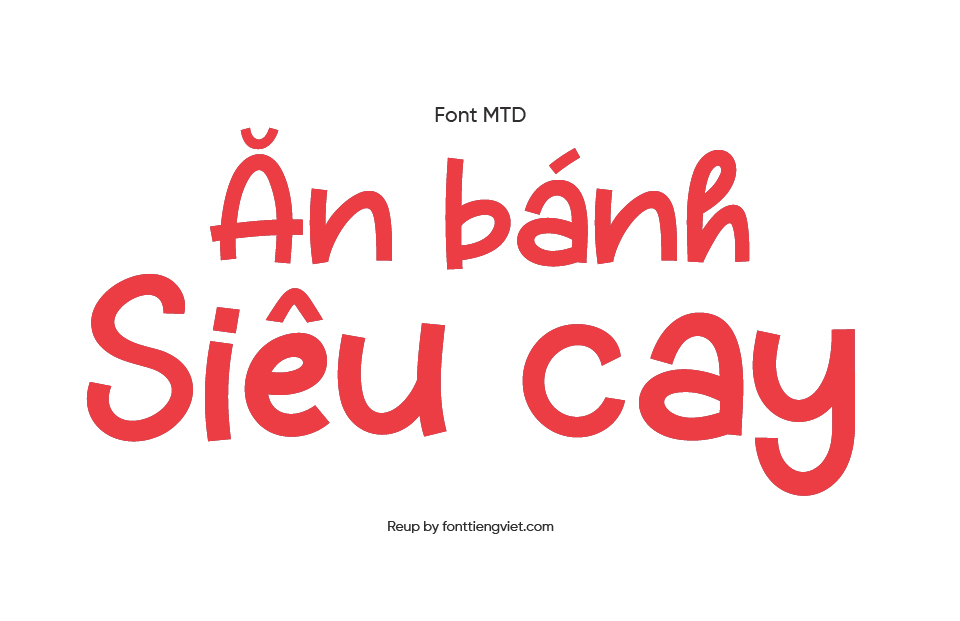
Trong thế giới thiết kế đồ họa và sáng tạo nội dung số, việc lựa chọn Font Chữ phù hợp đóng vai trò then chốt trong việc truyền tải thông điệp. Một xu hướng nổi bật gần đây là việc sử dụng các phông chữ thủ công (handwritten) hoặc phông chữ hiển thị (display font) với phong cách độc đáo, tươi mới. Chính vì lẽ đó, cộng đồng thiết kế Việt Nam đã đón nhận nồng nhiệt sự xuất hiện của Font Việt hóa MTD Cheese Sauce. Đây không chỉ là một phông chữ thông thường, mà còn là một công cụ giúp các bạn học sinh, sinh viên, đặc biệt là những người đang chuẩn bị cho các đồ án tốt nghiệp hoặc bài thuyết trình quan trọng, nâng cao tính thẩm mỹ và sự chuyên nghiệp cho tác phẩm của mình. Phông chữ này đã được Việt hóa kỹ lưỡng, đảm bảo khả năng hiển thị hoàn hảo các ký tự tiếng Việt có dấu, mang lại sự linh hoạt tối đa cho người dùng.
Khám Phá Sức Hút Đặc Biệt Của Font Việt hóa MTD Cheese Sauce
MTD Cheese Sauce là một phông chữ mang đậm chất cá nhân hóa, thường được xếp vào nhóm phông chữ viết tay (handwritten) hoặc brush script. Điểm mạnh lớn nhất của nó nằm ở sự ngẫu hứng và nét cọ mạnh mẽ, mô phỏng chân thực cảm giác viết bằng tay. Khi được “Việt hóa” (chuyển đổi và bổ sung các ký tự tiếng Việt), Font Việt hóa MTD Cheese Sauce không chỉ giữ nguyên được linh hồn ban đầu mà còn trở nên hữu ích hơn gấp bội cho thị trường nội địa. Sự Việt hóa chuyên nghiệp đảm bảo rằng tất cả các dấu thanh, dấu mũ, và các ký tự đặc biệt của tiếng Việt đều được tích hợp mượt mà, không gây lỗi hiển thị hay mất cân đối về mặt thị giác (optical balance). Phông chữ này rất phù hợp với các thiết kế đòi hỏi sự vui tươi, năng động, và một chút phá cách, ví dụ như thiết kế bao bì sản phẩm, thiệp mời sự kiện, hay các ấn phẩm quảng cáo dành cho giới trẻ.
Tại Sao Học Sinh, Sinh Viên Cần Quan Tâm Đến Phông Chữ Này?
Đối với học sinh cấp ba và sinh viên đại học, việc tạo ra các bài tiểu luận, báo cáo hoặc đồ án có tính thẩm mỹ cao ngày càng trở nên quan trọng. Một phông chữ độc đáo như MTD Cheese Sauce có thể giúp bài thuyết trình của bạn nổi bật hơn giữa đám đông. Thay vì chỉ sử dụng các phông chữ phổ thông, việc áp dụng phông chữ này vào các tiêu đề, trích dẫn nổi bật hoặc các tài liệu quảng bá cho câu lạc bộ sẽ tạo ra dấu ấn mạnh mẽ. Các dự án nghệ thuật, tạp chí tường, hay thiết kế áo lớp cũng là những ứng dụng hoàn hảo cho phông chữ mang phong cách typography hiện đại này. Sử dụng phông chữ Việt hóa chất lượng cao giúp tiết kiệm thời gian chỉnh sửa lỗi font, cho phép sinh viên tập trung hơn vào nội dung cốt lõi của bài thi hoặc bài báo cáo cuối kỳ.
Ứng Dụng Thực Tiễn Của Phông Chữ Này Trong Học Tập và Thiết Kế
Khả năng ứng dụng của phông chữ Việt hóa MTD Cheese Sauce là rất rộng. Nó vượt ra ngoài phạm vi thiết kế đồ họa chuyên nghiệp và đi vào các hoạt động học thuật hàng ngày. Dưới đây là một số cách mà phông chữ này có thể hỗ trợ hiệu quả cho quá trình học tập và sáng tạo:
- Thiết Kế Poster và Infographic: Giúp các thông tin phức tạp trở nên dễ hiểu và hấp dẫn hơn, rất cần thiết cho các dự án nhóm trong môn Khoa học Xã hội hoặc các lớp Thiết kế Truyền thông.
- Đồ Án Tốt Nghiệp: Tạo điểm nhấn mạnh mẽ cho trang bìa hoặc các phần tiêu đề lớn trong đồ án, thể hiện sự đầu tư nghiêm túc vào mặt hình ảnh.
- Tài Liệu Marketing cho Trường Học/Sự Kiện Sinh Viên: Sử dụng trong các ấn phẩm quảng cáo cho ngày hội tuyển sinh, lễ tốt nghiệp, hay các chương trình ngoại khóa, mang lại cảm giác trẻ trung và thân thiện.
Sự ra đời của các phông chữ độc đáo như MTD Cheese Sauce, được Việt hóa hoàn chỉnh, đã làm phong phú thêm kho tàng tài nguyên thiết kế cho người Việt. Nó khuyến khích sự sáng tạo và giúp thế hệ học sinh, sinh viên hiện đại thể hiện cá tính mạnh mẽ hơn qua các sản phẩm học thuật và cá nhân của mình. Khả năng tương thích cao với các phần mềm phổ biến như Adobe Photoshop, Illustrator, PowerPoint và thậm chí là Google Slides làm cho phông chữ này trở thành lựa chọn lý tưởng cho mọi đối tượng người dùng.
Tóm lại, việc sở hữu và sử dụng Font Việt hóa MTD Cheese Sauce là một quyết định sáng suốt cho bất kỳ dự án thiết kế nào đòi hỏi sự độc đáo và cá nhân hóa cao. Từ việc tạo poster, thiết kế bìa sách, hay thậm chí là các tài liệu học tập sáng tạo, phông chữ này mang lại giá trị thẩm mỹ vượt trội. Hãy đảm bảo bạn tải về phiên bản Việt hóa chất lượng để tối ưu hóa việc sử dụng tiếng Việt và tuân thủ các quy tắc bản quyền. Nếu bạn đang tìm kiếm thêm các lựa chọn Font Chữ độc đáo khác để làm phong phú bộ sưu tập của mình, hãy truy cập các nguồn uy tín để khám phá thêm nhiều tuyệt phẩm typography phục vụ cho kỳ thi tốt nghiệp hoặc các dự án quan trọng sắp tới. Đừng ngần ngại thử nghiệm sự kết hợp giữa sự sáng tạo của phông chữ này và sự nghiêm túc của nội dung học thuật bạn đang truyền tải.